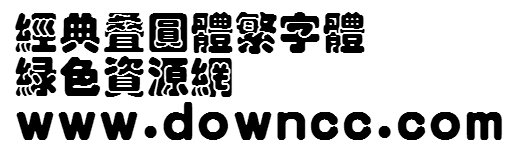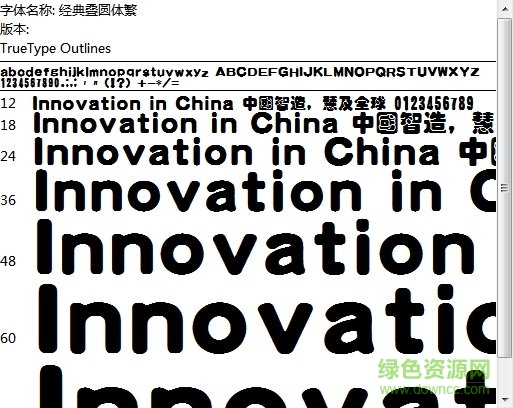
經(jīng)典疊圓體繁是經(jīng)典圓體簡(jiǎn)字體的繁體格式,支持更多繁體漢字輸入,讓用戶(hù)可以更大范圍的使用該款字體,文字需要在繁體狀態(tài)下使用,需要的朋友就來(lái)綠色資源網(wǎng)試試吧!
經(jīng)典疊圓體繁體,這款字體有很強(qiáng)的藝術(shù)設(shè)計(jì)感,字體線(xiàn)條較粗,連接部分用空心展示,是一款非常實(shí)用的中文字體。
經(jīng)典疊圓繁體是一款適用于繁體中文的疊圓字體下載,也是經(jīng)典字體系列之一,字體非常粗壯,但字形端正大方,字庫(kù)完整,可應(yīng)用于雜志報(bào)刊、文學(xué)創(chuàng)作、平面廣告、印刷包裝等領(lǐng)域!